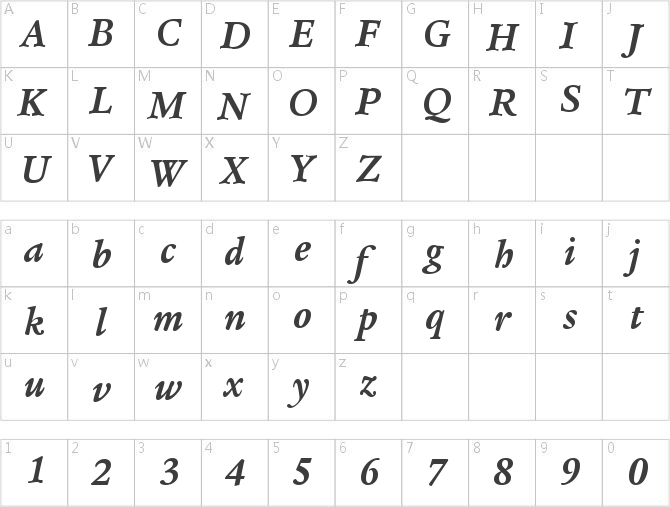
Legacy-Serif-ITC-TT-BoldItalic 詳情頁
Legacy-Serif-ITC-TT-BoldItalic字體字庫是一款讓人賞心悅目、百看不厭的英文字體,適合各類廣告和產(chǎn)品包裝設(shè)計應(yīng)用,字體大小0.08MB,格式為ttf字體,上傳用戶是浪跡天涯,作者/版權(quán)方為未知